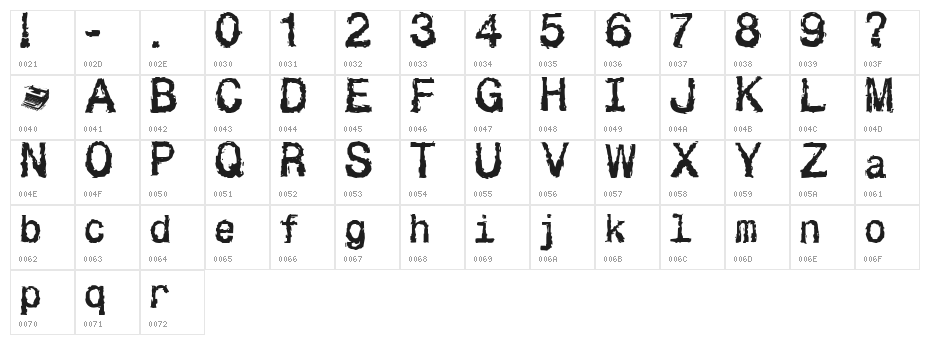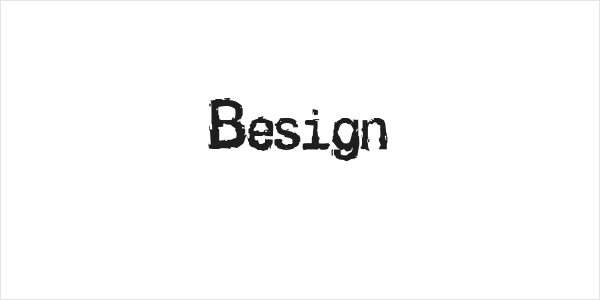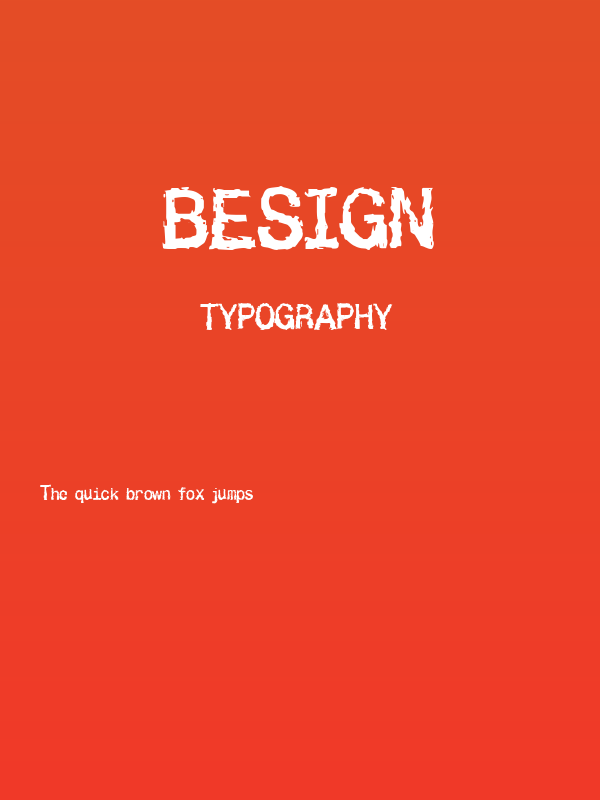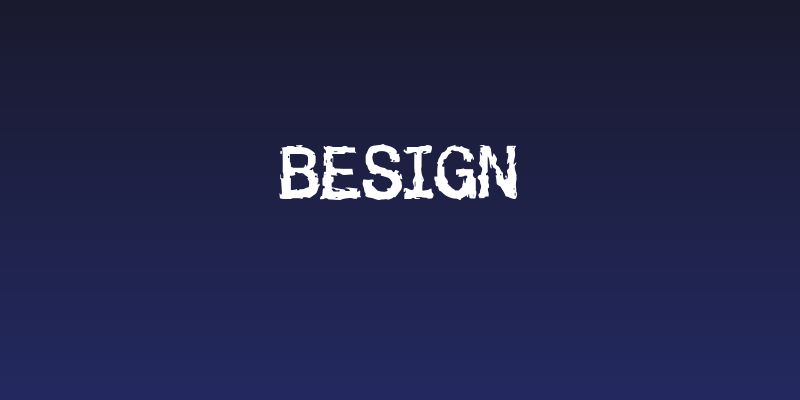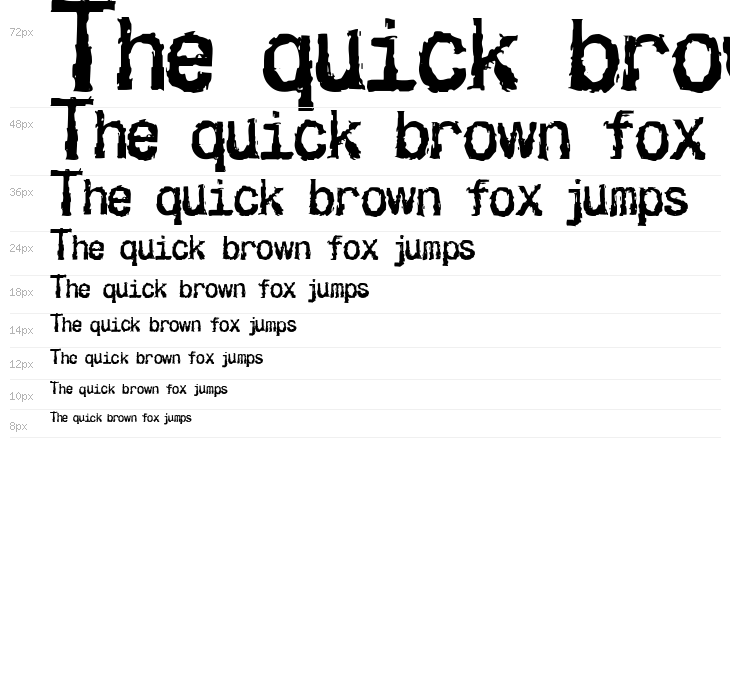
Besign Font
✎ Distorted Eroded
| Kategorien | Distorted Eroded |
| Anwendungsfall | Logos, Headlines, Posters |
| Vorgeschlagene Projekte | Ideal for album covers, posters, street art designs, and branding projects that require a bold, edgy aesthetic. |